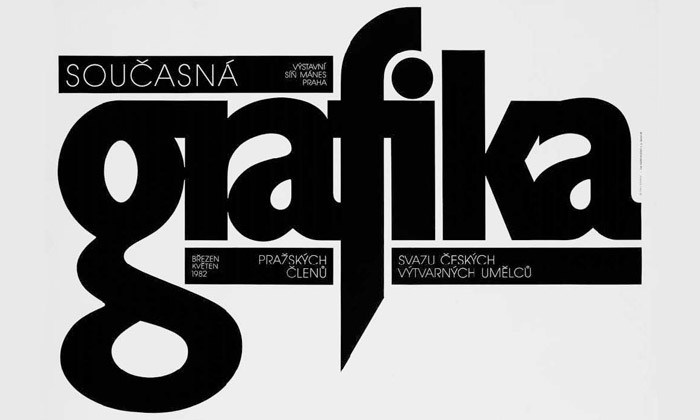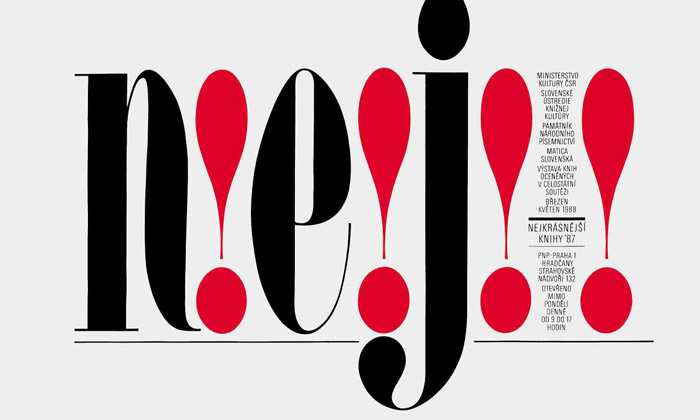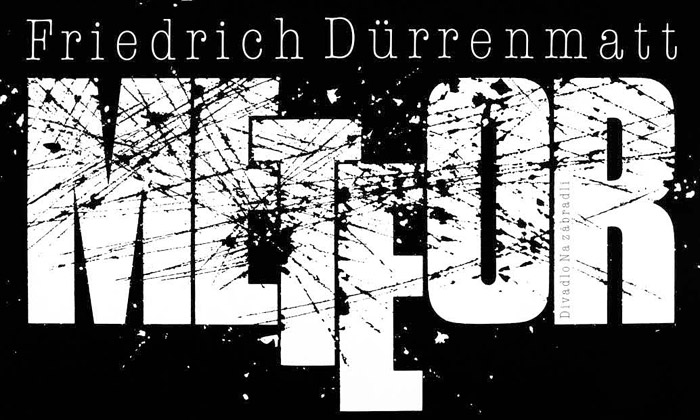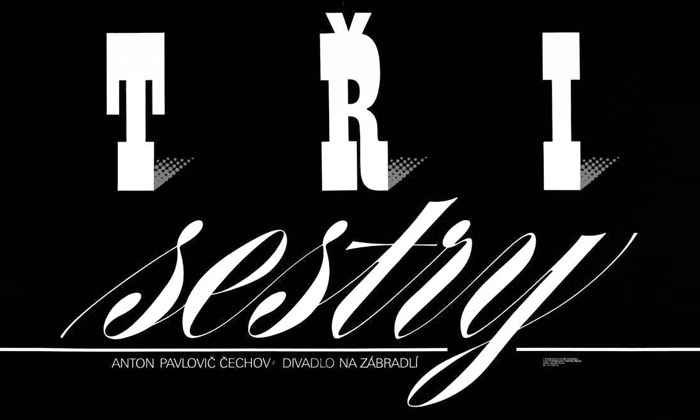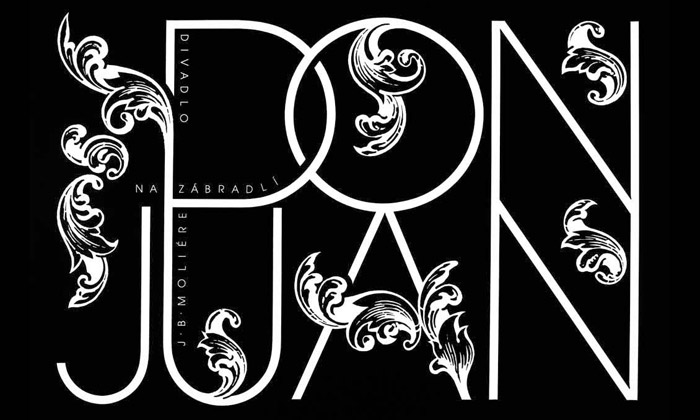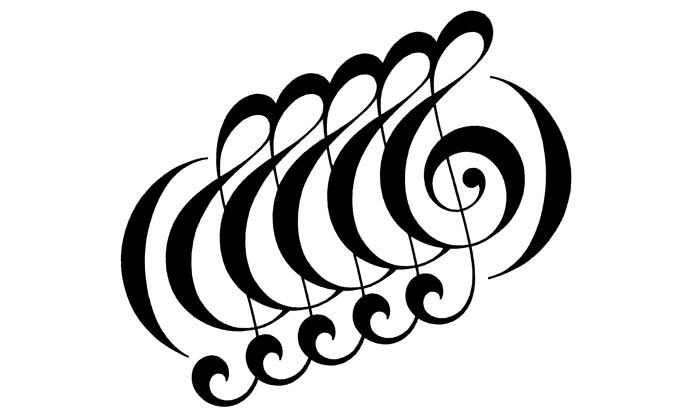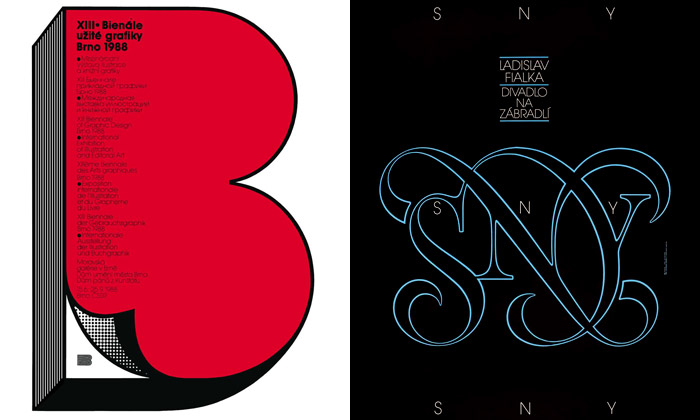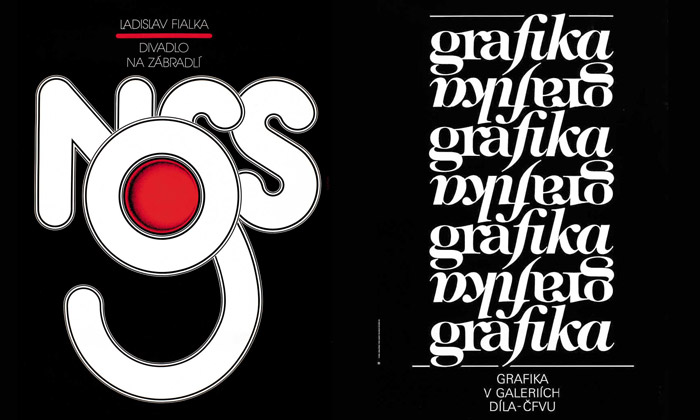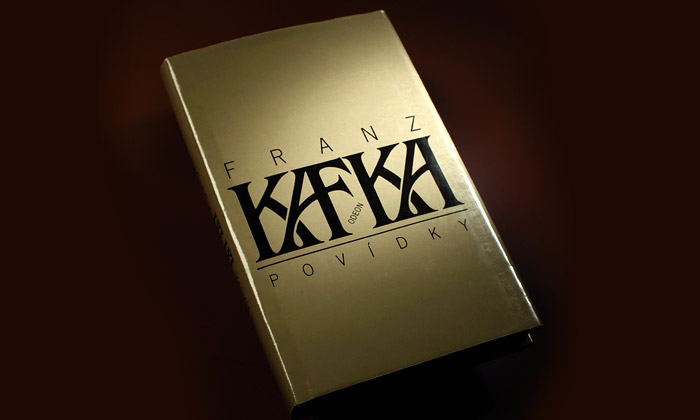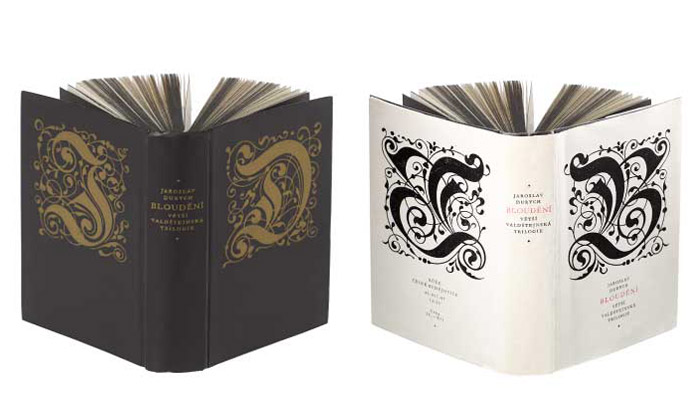
V rámci 24. Mezinárodního bienále v Brně, v sekci Osobnosti českého grafického designu, letos představují průřez tvorbou předního českého grafika, zabývajícího se především tvorbou písem, log a plakátů. Jan Solpera, ač to sám nerad přiznává, patří ke „klasikům“ českého grafického designu. Výstava je již druhou letošní retrospektivou k jeho významnému životnímu jubileu.
K výstavě vychází zdařilý katalog s názvem „… jen písmena a číslice“. Většinu prací sám autor opatřil kratičkým textem, kde se zmiňuje o inspiraci nebo o zajímavostech, které se k dílu vztahují. Katalog se tak stává zážitkem nejen vizuálním, ale také příjemným zprostředkováním upřímného pohledu na jeho tvorbu jako takovou.
Jak vnímáte současnou digitalizaci, to, že si může každý pořídit počítač a využívat jednoduše profesionální grafické nástroje?
Patřím k té generaci, která veškerou svojí práci dělala bez počítačů. Nedovedu na obrazovce myslet. Já, když dělám nějakou konkrétní věc, ji musím udělat na papír rukou. Třeba ve formě skici. Ale nedovedu přímo na monitoru tu věc udělat jako takovou, dotáhnout ji do té formy, jak to dokážou mladší generace a vlastně všichni mí studenti. Pro mě je počítač pomocník, nikoli spolupracovník.
Myslím si, že počítače jsou báječná věc. A do teď lituju, že jsem si je po té technické stránce víc neochočil. Vím, co od nich můžu chtít, ale nedovedu s nimi zacházet, aby mi sloužily tak, jak mi slouží štětec nebo tužka. Ale znovu říkám, je to generační záležitost.
Asi máte tu výhodu, že jste zažil období bez monitorů. My už bez nich nedokážeme myslet.
Já si myslím, že je to naopak moje nevýhoda…
V katalogu, který k výstavě vychází, píšete, že jste hodně využíval černou a bílou proto, že tehdy byla kvalita tisku výrazně horší. Takže ty černobílé plakáty vycházely lépe než ty barevné?
To nebyla otázka jenom digitalizace. To byla před listopadem otázka úrovně polygrafického průmyslu. Když jsem na tyhle výstavy vybíral knížky, kterých jsem udělal poměrně hodně, tak všechny byly úděsně blbě vytištěny. Teď vám i ta nejmenší tiskárnička dovede na dokonalém papíru odvést poměrně slušný tisk, což se nedá srovnat s tím, jak tehdy tiskly takzvaně špičkové podniky. Pro mě to bylo takové jakoby, nechci říci východisko z nouze, že mě vždycky ten kontrast černé a bílé velice zajímal a byl příjemný. Zároveň jsem měl jistotu, že ten plakát bude doopravdy takový, jak ho udělám.
Takže příchod kvalitnějších tiskových technik neznamenal pro vaší tvorbu boom barevnosti?
Ne, to vůbec ne. I proto jsem se nechtěl moc s počítačem skamarádit, chtěl jsem, aby to moje myšlení zůstalo takové, jaké je. Je to sice konzervativní, ale znáte to – starého psa těžko naučíte novým kouskům.
Dlouho jste učil písmo na Vysoké škole uměleckoprůmyslové v Praze, kde jste také studoval. Vzpomínáte na svá studentská, šedesátá léta?
Na první pokus jsem se nedostal. Bylo mi jasné, že musím ještě hodně kreslit. Rok jsem také vystřídal několik zaměstnání, jedno také v tiskárně, kde jsem rejpal do linolea. Tam jsem si uvědomil, že nechci být někde, kde musím vstávat na šestou, to bylo utrpení. Na podruhé už mě vzali, a byl jsem za to rád. Tehdá jsme byli v ročníku tři.
Jak se díváte na dobu komunismu?
Pořád to byl tanec v minovém poli. Naštěstí do těch písmenek nikdo moc nemluvil. Písmenka nebyla tak problematická jako výtvarný prvek.
Na škole jsem si uvědomil, že můžu zkusit vést ateliér podle své představy a ne podle představy vedení školy.
Jak tehdy fungoval vztah klient – grafik?
Měl jsem to štěstí, že jsem se nemusel moc podbízet. Zajímavé je, že když jste se setkal s blbcem, který byl v nějaké funkci, tak to byl podobná typ blba, jako je teď ten, který má hodně peněz.
Knížka, která k výstavě vznikla, se jmenuje …jen písmena a číslice, což je v souvislosti s vaší prací podle mě pochopitelné, srozumitelné a čitelné označená. Myslíte si, že právě tato slova vyjadřují vaši tvorbu?
Určitě, ke mně ta písmenka v raném období docela mluvila. Uvědomoval jsem si rozdíl v tom, že některé to písmo působí třeba agresivněji než jiné. Ten pocit z formy písma jsem vnímal docela brzo.
Vaše poslední retrospektiva se jmenovala Space Cowboy. Jak tento název vznikl?
To začalo tím, že Karel Haloun a Luboš Drtina za mnou přišli a říkali, že se ještě s Frantou Štormem dohodli, že by mi chtěli udělat výstavu. A já říkám, že jsem na to línej. A oni, že se nemám o nic starat, že to zadají ve škole jako úkol. Šel jsem se na to kouknout až po klauzurách, a byl to docela šok – brali mě jako „klasika“.
A jeden kluk si tam vzal moje široká tučná písmenka a přidal motiv Space Cowboy, a to bylo ono. Já vlastně chodím dvacet let takhle (ukazuje na svou „kovbojskou“ košili se sedlem), v džínech a džínových košilích.